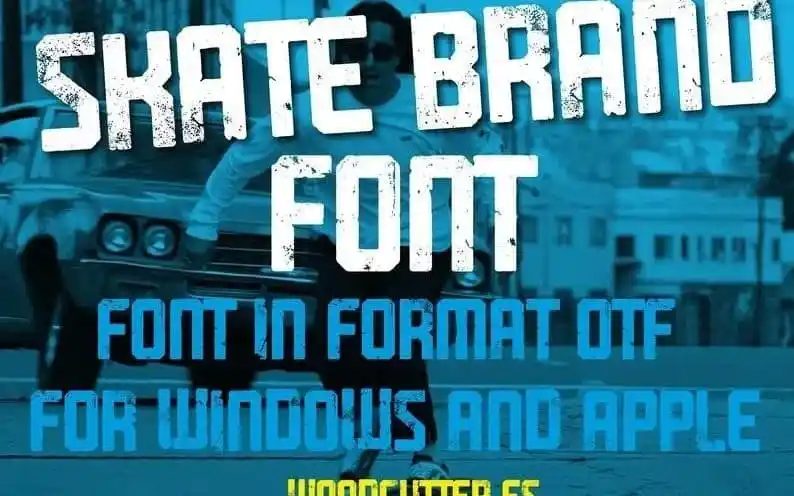
Skate Brand Display Font – Download Grátis
A Skate Brand Display Font é uma escolha perfeita para quem busca incorporar um estilo clássico e moderno em seus projetos digitais. Com seu risco livre pura, a fonte oferece opções alternativas que permitem personalizações variadas. Seu caráter forte e limpo lhe dá liberdade de expressão, enquanto seu ar natural de pontas finas remete à impressão manual antiga, criando um visual autêntico e memorável em qualquer aplicação. Ideal para identidades visuais que buscam uma personalidade única no meio do design atual, a Skate Brand Display é uma escolha sólida para qualquer projeto que valorize o equilíbrio entre simplicidade e originalidade. Não perca esta oportunidade de adicionar um toque distintivo à sua próxima criação com nossa fonte de marca Skate Brand Display Font.